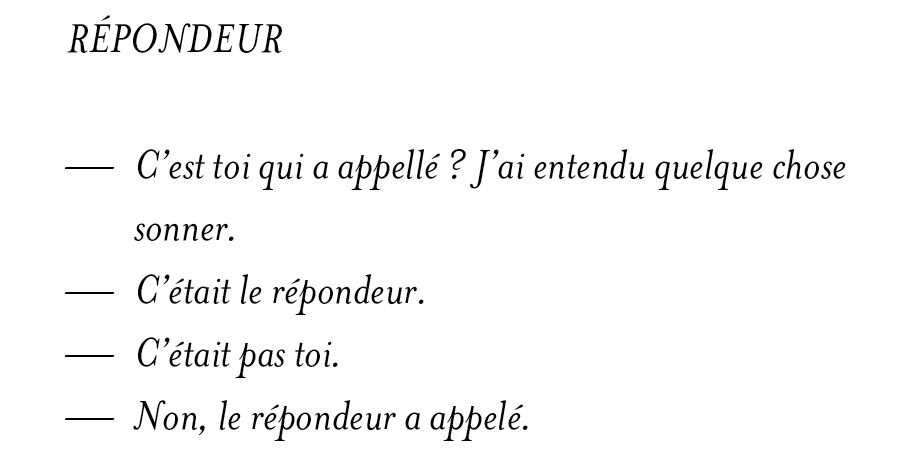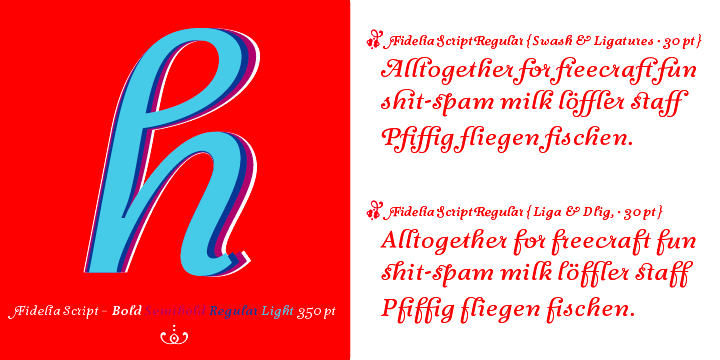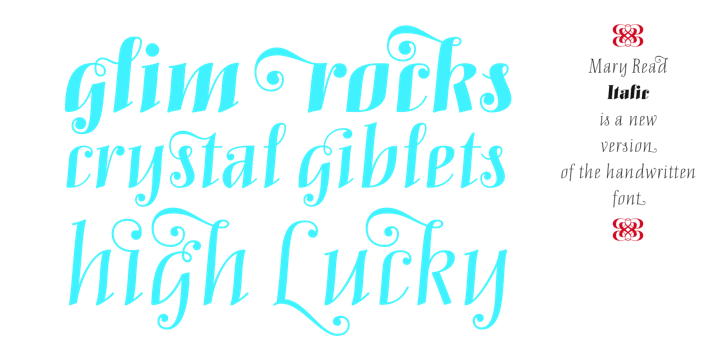
Schmuck-Kursive
Ich weiß nicht, ob es den Ausdruck der "Schmuck-Kursive" gibt, aber kennt ihr eine Schrift, die in diese Richtung geht? Einen Anfang habe ich schon, die Mrs Eaves Italique:
Also eine Kursive mit viel Geschnörkel und Verzierungen. Aber keine Brush oder Script, sondern etwas dazwischen.
ist glaub ich zu viel des Guten .. etwas weniger verspielt wäre besser, eben so zwischen seriös und volle Kante extrovertiert.
ist glaub ich zu viel des Guten .. etwas weniger verspielt wäre besser, eben so zwischen seriös und volle Kante extrovertiert
:tuschel: Hast Du Dir auch schon die ersten drei Vorschläge oben angesehen? Die haben auch je eine Kursive ohne „Schmuck“. Diese kann man dann nach Belieben mit Schmuckbuchstaben (siehe Swash-Schnitte) garnieren, oder eben auch „pur“ verwenden. :-D
Viele Klassiker wie z.B. Minion und Adobe Garamond haben u.a. in der Pro Version auch welche in den Kursiven und die fallen nicht so sehr auf.
Super Tipp, vielen Dank. Die der Caslon Pro sind auch schön schnörkelig.